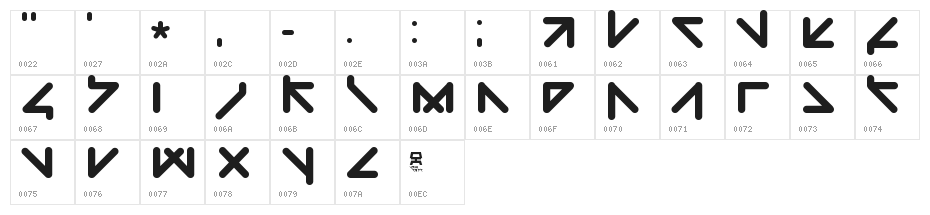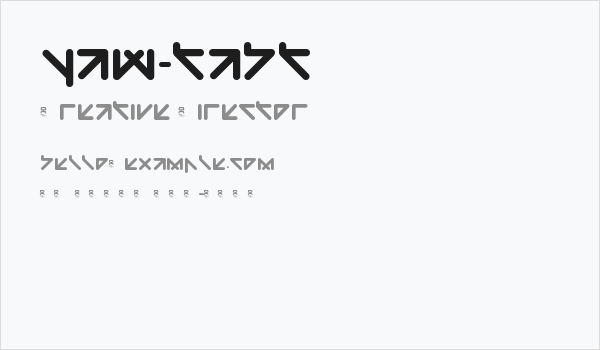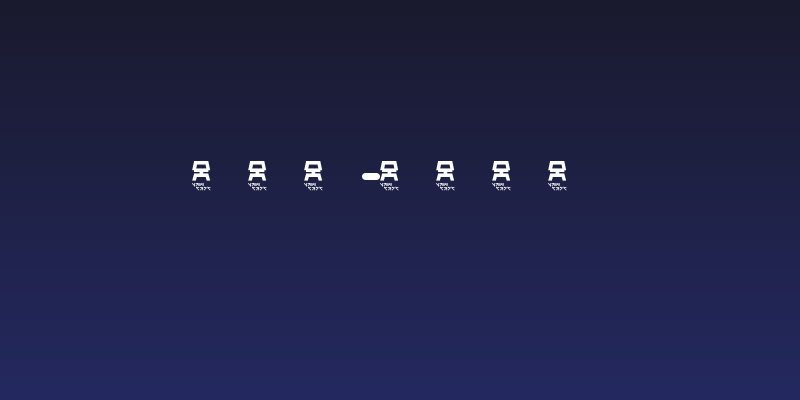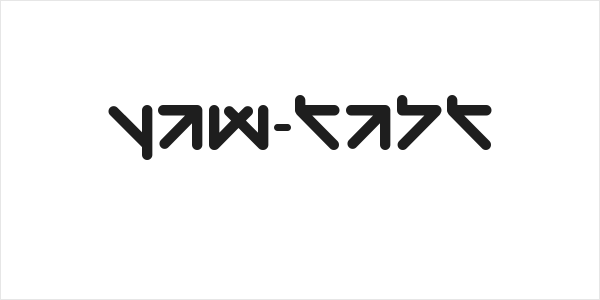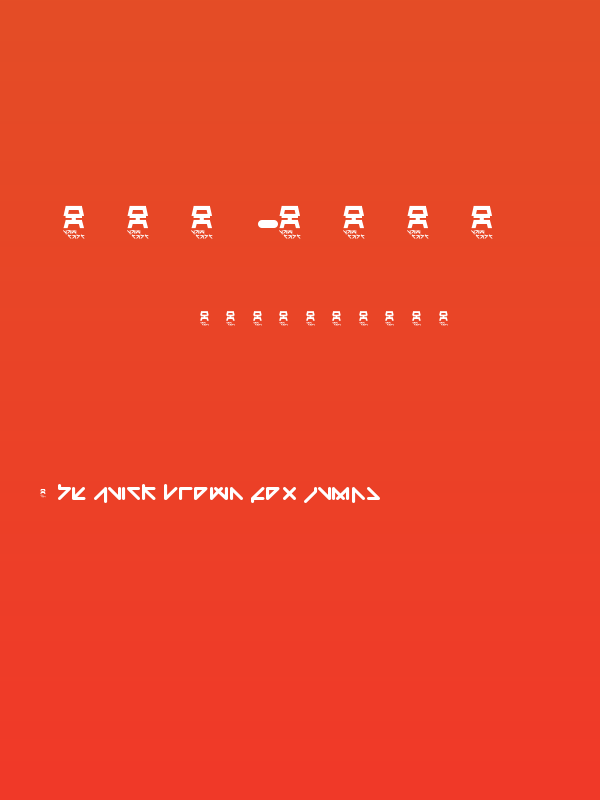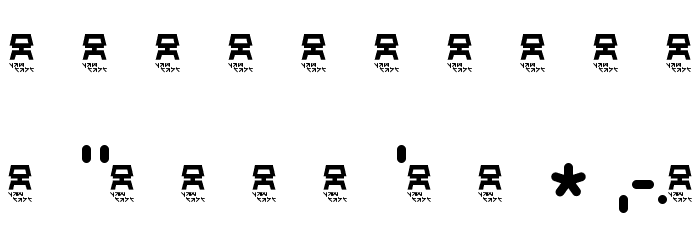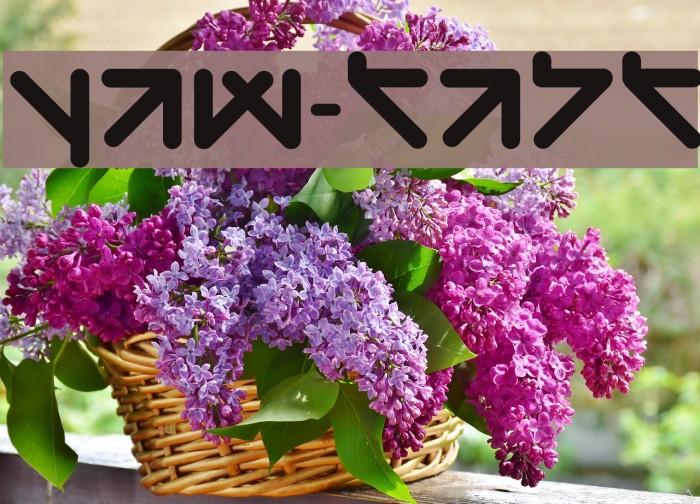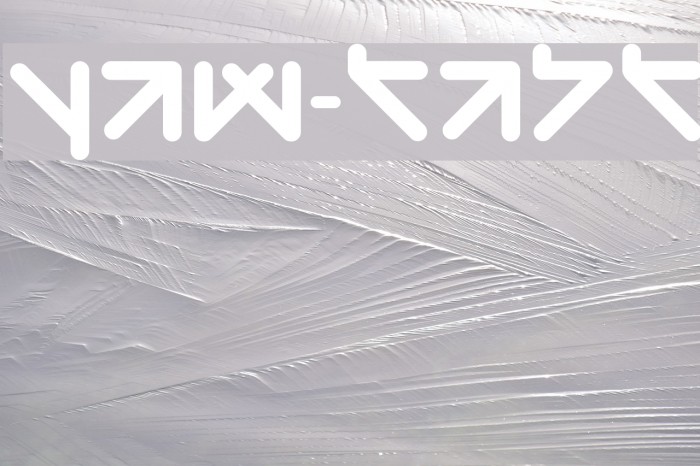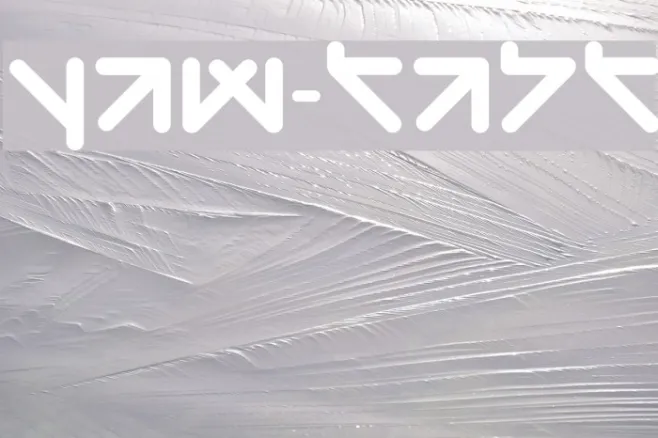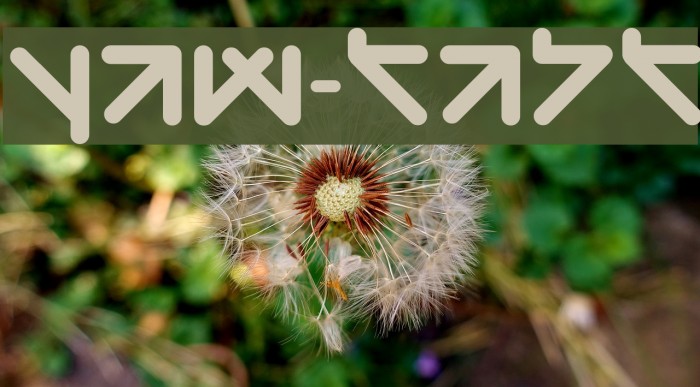
yaw-taht Font
| Gesamtstil | Futuristic |
| Anwendungsfall | Logos, Headlines, Posters |
| Vorgeschlagene Projekte | Ideal for sci-fi themed designs, video game graphics, tech branding, and futuristic posters. |